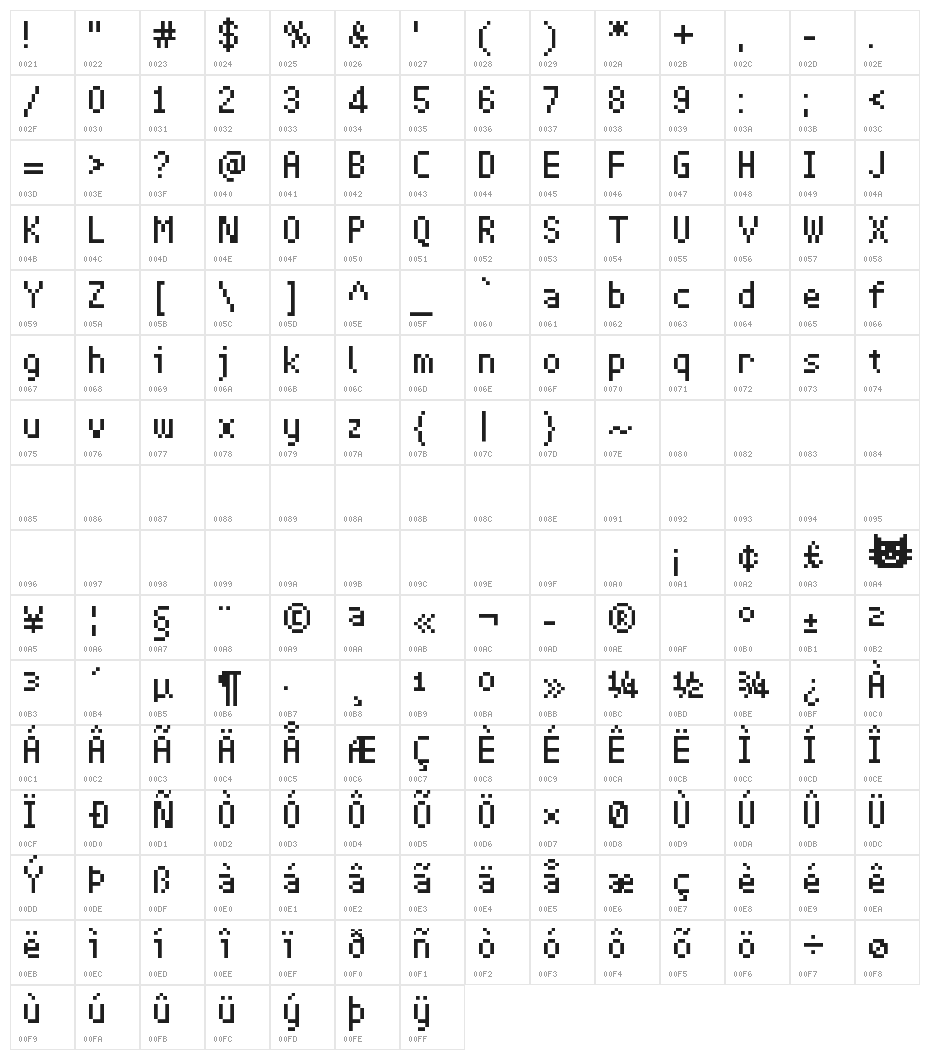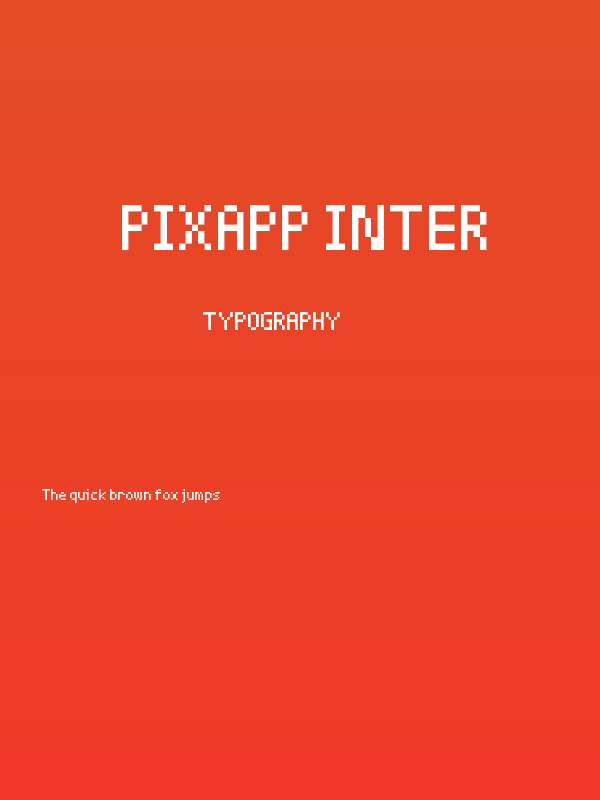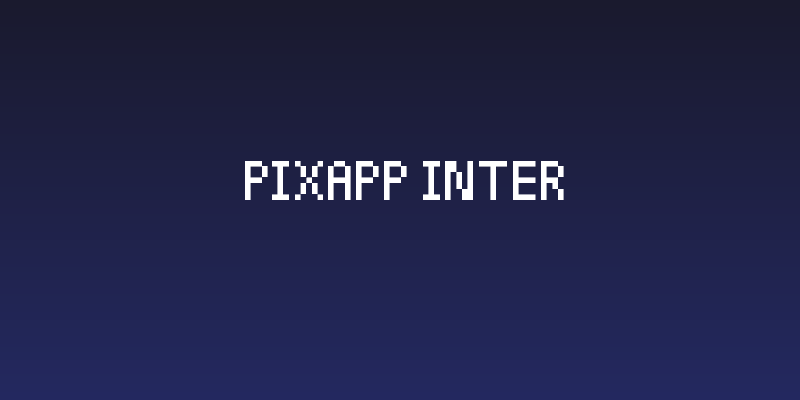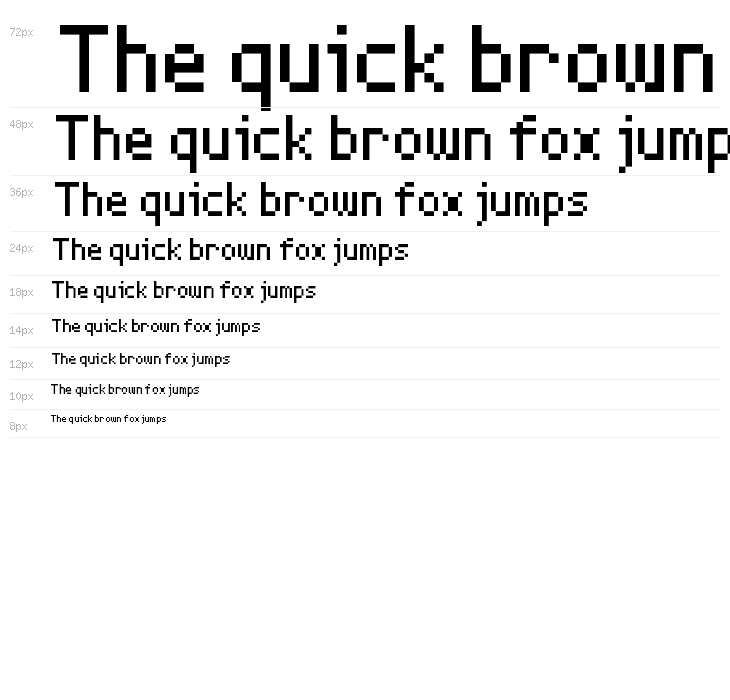
Pixapp Inter Font
| Stile generale | Retro, Digital |
| Caso d'uso | Logos, Headlines, Digital Art |
| Progetti proposti | Ideal for video game design, digital art projects, retro-themed websites, and tech-related branding. |